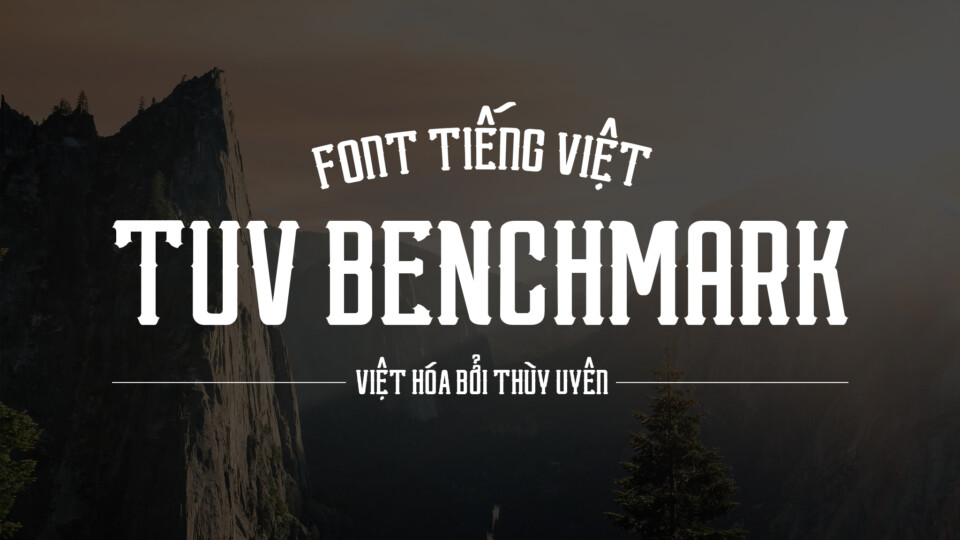
Giới thiệu về Font Việt hóa TUV Benchmark – Việt hóa bởi Thùy Uyên
Trong thế giới đồ họa hiện đại, việc lựa chọn Font Chữ phù hợp đóng vai trò then chốt tạo nên linh hồn cho tác phẩm. Font Việt hóa TUV Benchmark – Việt hóa bởi Thùy Uyên là một bộ phông đặc biệt, được chau chuốt kỹ lưỡng để phục vụ cộng đồng designer Việt. Với đường nét thanh thoát nhưng không kém phần mạnh mẽ, bộ font này nhanh chóng trở thành lựa chọn ưu tiên cho các dự án yêu cầu sự chuyên nghiệp và tính thẩm mỹ cao.
Đặc điểm nổi bật của font Benchmark
TUV Benchmark sở hữu cấu trúc hình học cân đối, giúp văn bản trở nên dễ đọc và bắt mắt. Bản Việt hóa bởi Thùy Uyên đã xử lý hoàn hảo các dấu tiếng Việt, đảm bảo không bị lỗi hiển thị khi đánh máy. Điều này giúp các bạn học sinh và giáo viên dễ dàng ứng dụng vào việc làm slide bài giảng hoặc trình bày báo cáo một cách sinh động nhất.
Ứng dụng thực tế của Font Việt hóa TUV Benchmark – Việt hóa bởi Thùy Uyên
Bộ font này cực kỳ đa năng, phù hợp cho nhiều mục đích sử dụng khác nhau trong môi trường giáo dục và sáng tạo. Bạn có thể dùng Font Việt hóa TUV Benchmark – Việt hóa bởi Thùy Uyên để thiết kế bìa sách, làm tiêu đề cho các tờ báo tường hoặc tạo ra những tấm thiệp chúc mừng độc đáo. Sự tinh tế trong từng nét chữ sẽ giúp thông điệp của bạn được truyền tải một cách trọn vẹn và ấn tượng hơn bao giờ hết.
Lưu ý khi sử dụng font trong thiết kế
Dù là một font chữ đẹp, người dùng cần lưu ý kết hợp Benchmark với các font không chân khác để tạo sự tương phản. Việc sử dụng đúng kích thước và khoảng cách chữ sẽ giúp bản thiết kế đạt được độ thoáng cần thiết, tránh gây rối mắt cho người xem.